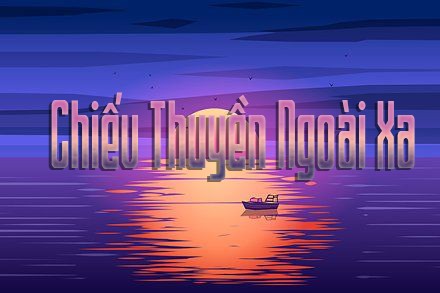
Giới thiệu về bộ Font việt hoá MJ HEAD UNIT
Trong thế giới thiết kế đồ họa hiện đại, việc tìm kiếm một bộ Font Chữ phù hợp để truyền tải thông điệp là vô cùng quan trọng. Font việt hoá MJ HEAD UNIT nổi lên như một lựa chọn hàng đầu cho những ai yêu thích phong cách mạnh mẽ, đậm chất kỹ thuật và hiện đại. Được chuyển ngữ tỉ mỉ sang tiếng Việt, bộ font này giúp người dùng dễ dàng thể hiện các nội dung văn bản mà không lo lỗi font hay thiếu dấu. Đây là công cụ hỗ trợ đắc lực cho các bạn học sinh trong việc làm báo cáo, thuyết trình hay các giáo viên thiết kế bài giảng sinh động.
Ưu điểm nổi bật của Font việt hoá MJ HEAD UNIT
Thiết kế tối giản và chuyên nghiệp
Đặc điểm nổi bật nhất của Font việt hoá MJ HEAD UNIT chính là những đường nét dứt khoát, hình khối vuông vức tạo cảm giác chắc chắn. Phong cách này cực kỳ phù hợp cho các tiêu đề sách, poster sự kiện trường học hoặc các biển báo hướng dẫn. Sự rõ ràng của từng ký tự giúp người đọc dễ dàng tiếp nhận thông tin ngay từ cái nhìn đầu tiên.
Khả năng ứng dụng đa dạng
Dù bạn đang thực hiện một dự án sáng tạo cá nhân hay bài tập nhóm, bộ font này đều đáp ứng tốt. Sự linh hoạt giữa các định dạng giúp nó tương thích hoàn hảo trên nhiều phần mềm thiết kế phổ biến. Việc sử dụng font chữ đẹp còn giúp nâng cao thẩm mỹ và tư duy sáng tạo cho học sinh trong quá trình học tập.